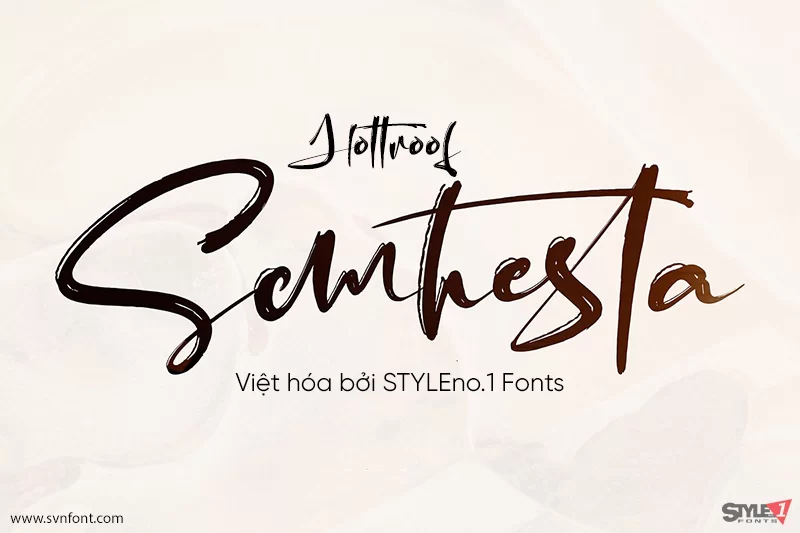
[Việt hóa] SVN-Hottroof Semhesta - Font chữ thư pháp mới nhất
Semhesta Brush Kiểu chữ viết tay, phông chữ này sẽ hoàn hảo cho nhiều dự án khác nhau: quotes, logo, blog header, poster, banding, fashion, apparel, letter, invitation, stationery,...